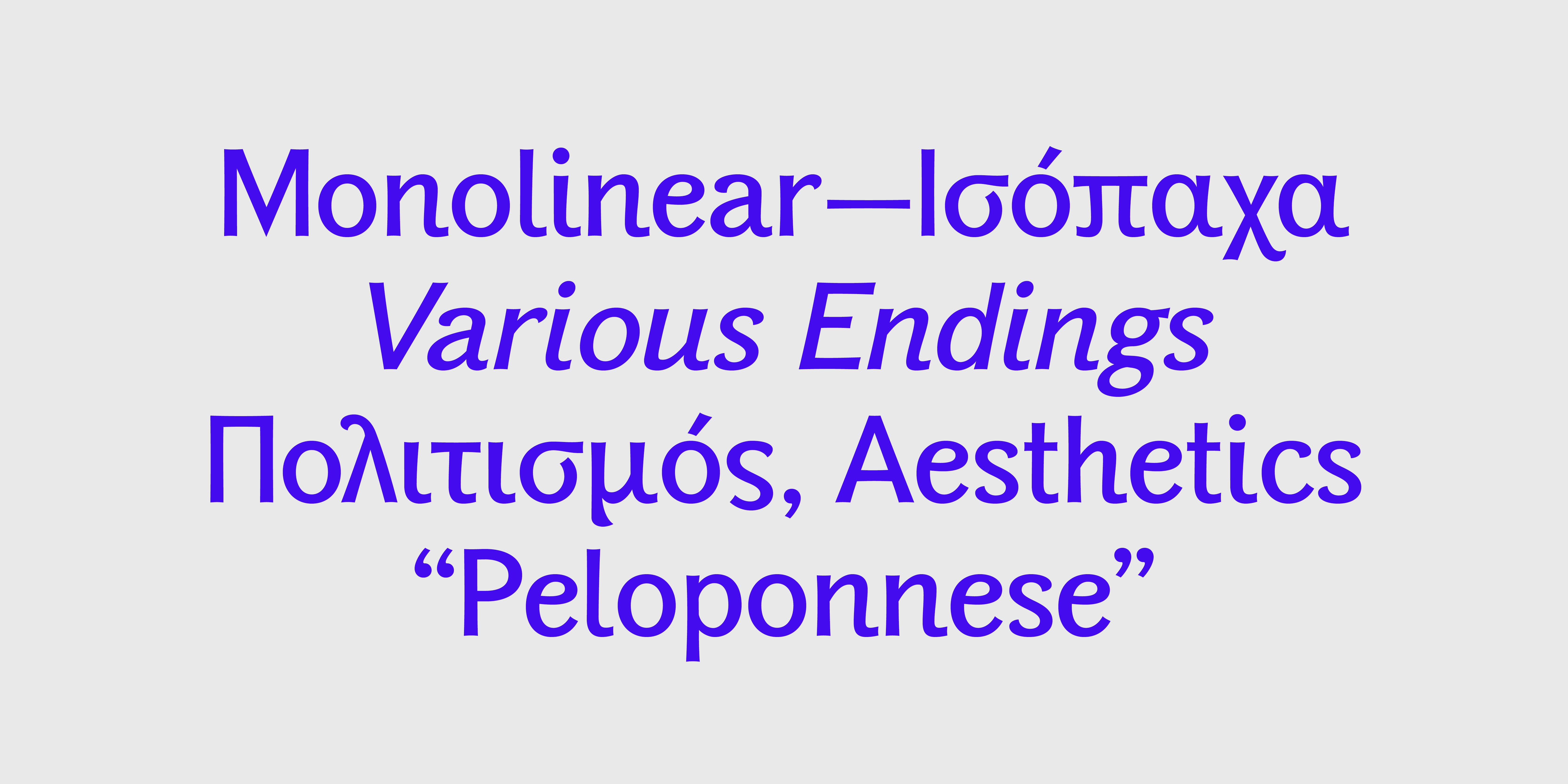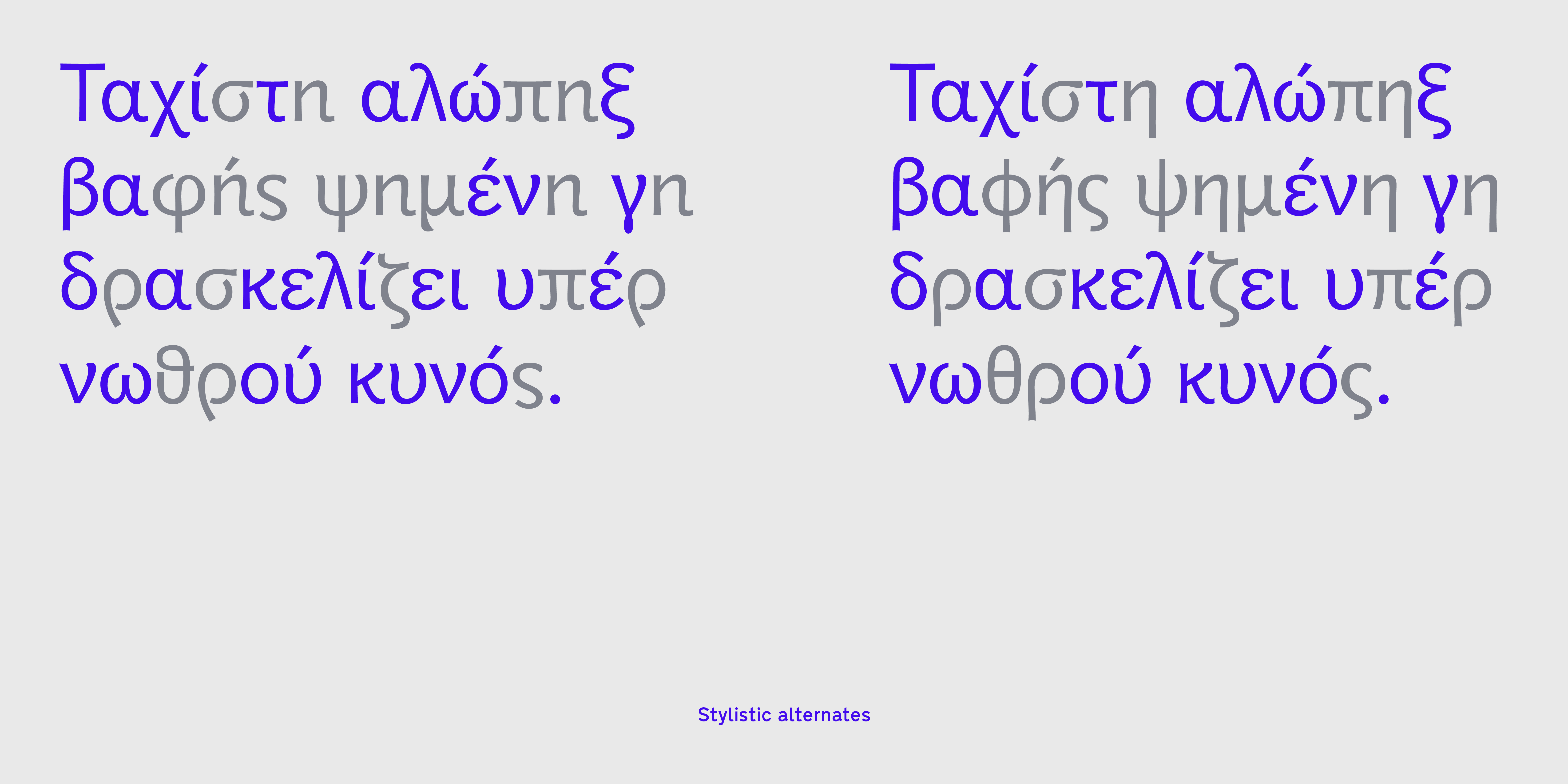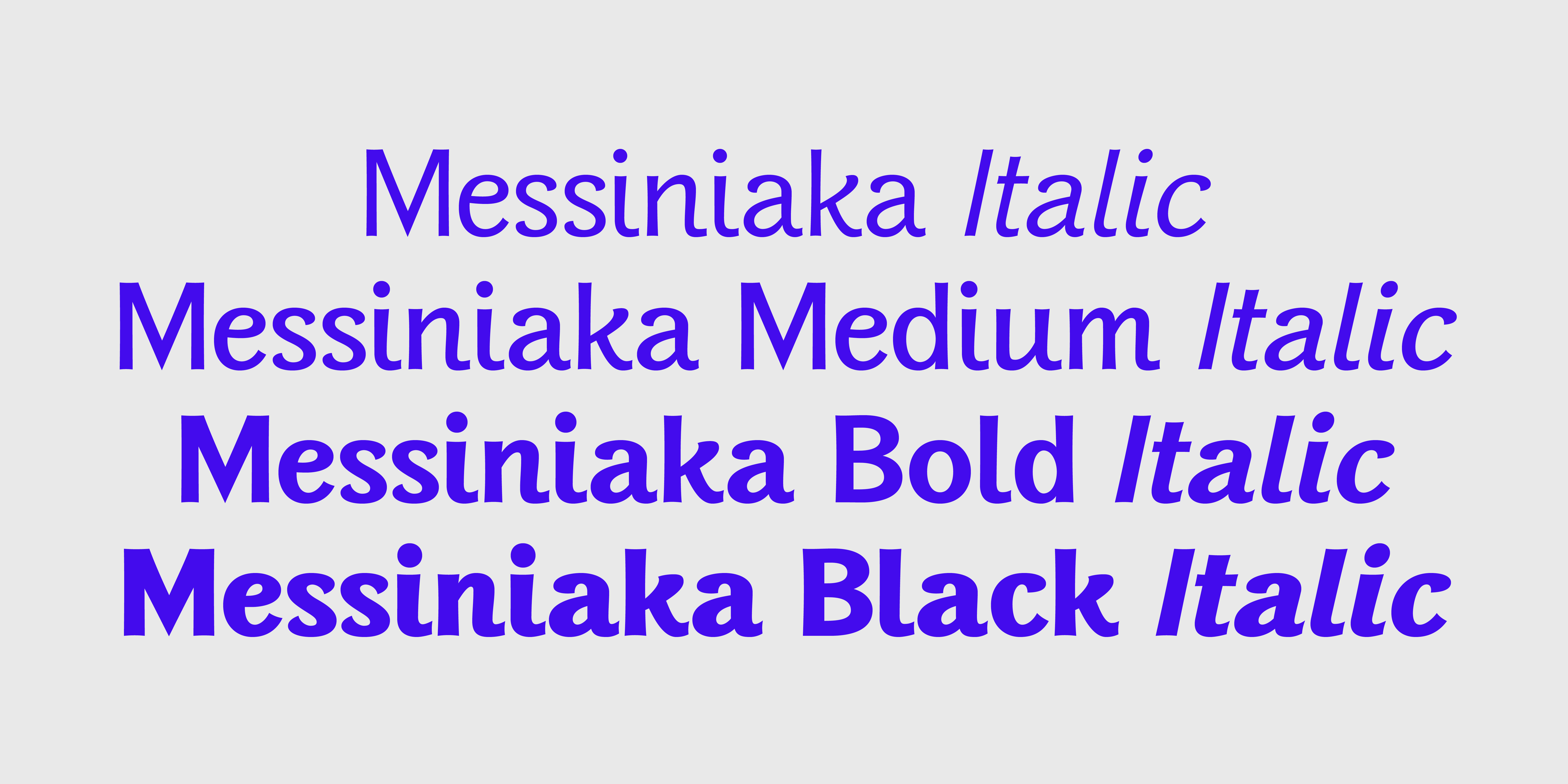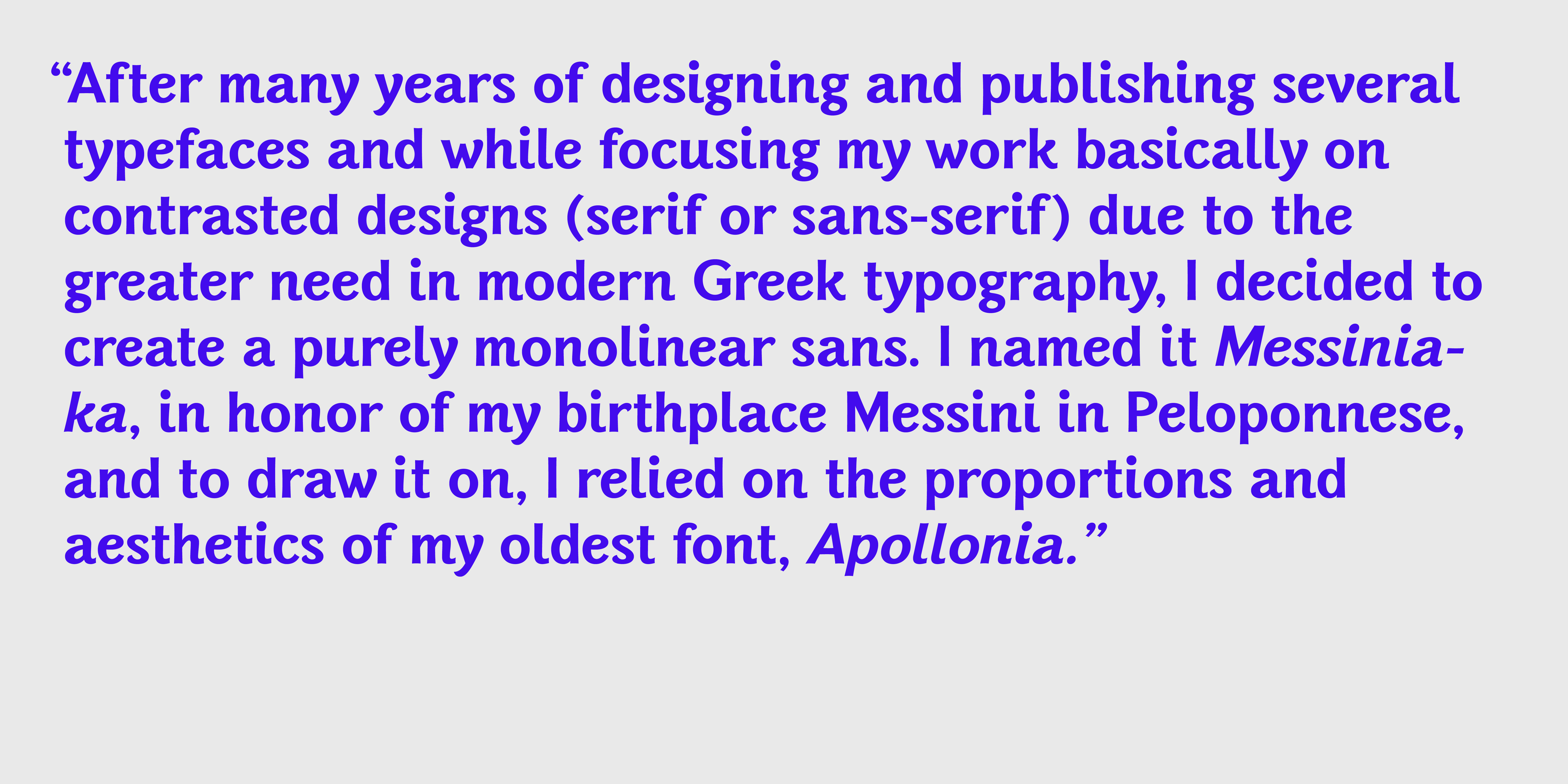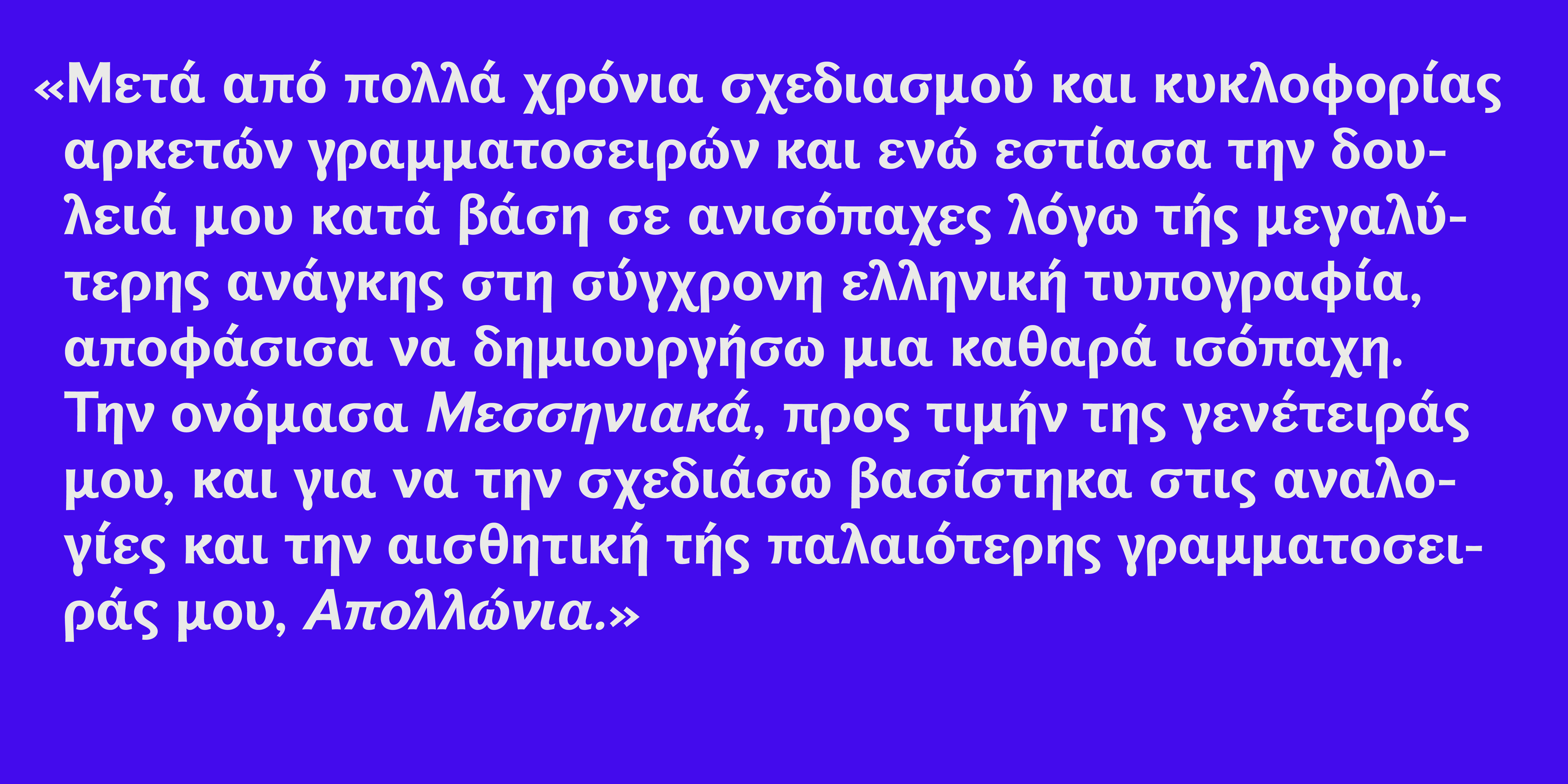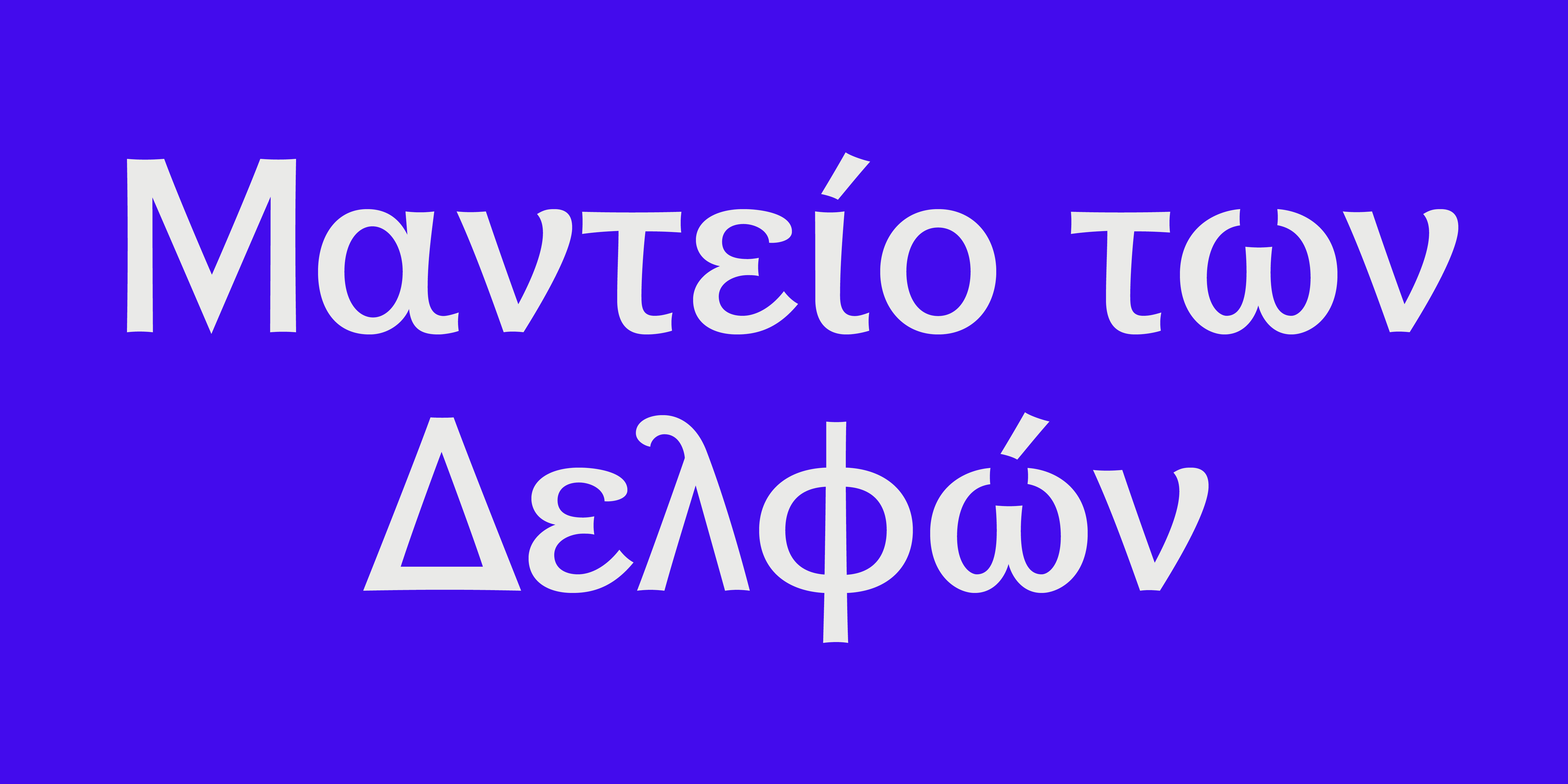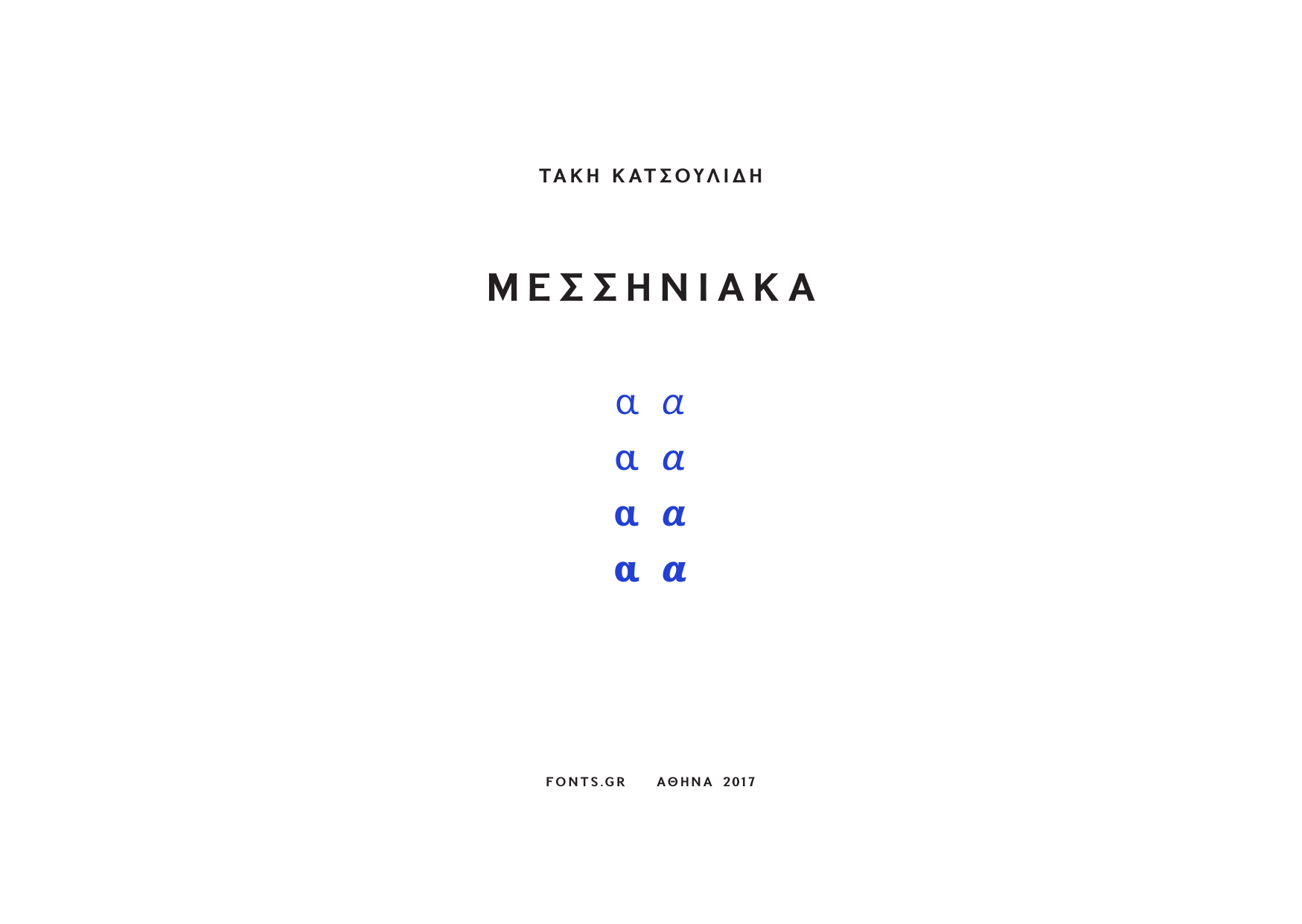
Messiniaka
Τάκης Κατσουλίδης: Μετά από πολλά χρόνια σχεδιασμού και κυκλοφορίας αρκετών γραμματοσειρών και ενώ εστίασα την δουλειά μου κατά βάση σε ανισόπαχες λόγω τής μεγαλύτερης ανάγκης στη σύγχρονη ελληνική τυπογραφία, αποφάσισα να δημιουργήσω μια καθαρά ισόπαχη. Την ονόμασα Μεσσηνιακά, προς τιμήν της γενέτειράς μου, και για να την σχεδιάσω βασίστηκα στις αναλογίες και την αισθητική τής παλαιότερης γραμματοσειράς μου, Απολλώνια. Στον ψηφιακό σχεδιασμό συνέβαλε ο Δημήτρης Μπόβολος, με τελική επιμέλεια των Βασίλη Γεωργίου και Παναγιώτη Χαρατζόπουλου.